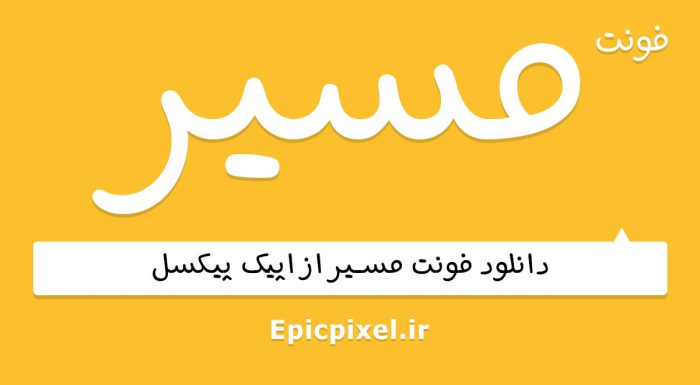
۵ فونت مسیر فارسی Massir
فونت های رایگان می توانند ابزارهای ارزشمندی برای طراحان باشند، به خصوص زمانی که سبک های متنوعی را ارائه می دهند. مجموعه ای که شامل سری فونت فارسی مسیر (A Massir) و نیز فونت های کلاسیک تر ابدو مسیر (Abdo Misr) است، چنین تنوعی را فراهم می کند. این مجموعه، فرصتی است تا با استفاده از سبک های متفاوت و کاربردی، به صورت رایگان، پروژه های خلاقانه خود را غنی تر کنید و جلوه ای خاص به طراحی های فارسی و عربی ببخشید.
کشف سری فونت های A Massir: سبکی الهام گرفته از دیوار نویسی
بیایید نگاهی دقیق تر به سری هنری A Massir داشته باشیم. این قلم فارسی اصالتاً یک فونت عربی بوده است که زحمت تبدیل و تطبیق آن برای زبان فارسی را آقای علی سواری کشیده اند. نکته برجسته و عاملی که فونت مسیر را از سایر فونت ها متمایز می کند، سبک بصری خاص و جسورانه آن است که به آن جلوه ای هنری و غیررسمی می بخشد و حالتی پویا و زنده به متن می دهد.
دو فونت از این سری که به صورت رایگان برای دانلود در دسترس هستند، با نام های A Massir Ballpoint Regular و A Massir Spray Regular ارائه می شوند. نام های این دو فونت خود گویای الهام گیری عمیق از حالت دیوار نویسی و اسپری رنگ هستند. در توضیحات این فونت به وجود دو نسخه کلی “ساده” و “دیواری نویسی شده” اشاره شده است؛ احتمالاً فونت های Ballpoint و Spray نمونه های برجسته یا زیرمجموعه هایی از سبک دیواری نویسی شده این خانواده هستند که با جزئیات و بافت های متفاوت ارائه شده اند تا شبیه سازی دقیق تری از نوشتار با قلم مو یا اسپری روی دیوار داشته باشند.
دانلودفونت مسیر با فرمت استاندارد و سازگار TTF ارائه شده و شامل تمامی حروف مورد نیاز زبان فارسی است. قابلیت استفاده در تمامی نرم افزارهای طراحی گرافیکی، این فونت گرافیکی را برای کاربردهای متنوعی چون طراحی های گرافیکی کلی، خلق لوگوتایپ های خاص و به یادماندنی، تیتر نویسی های چشمگیر در پوسترها و بنرها، و حتی آنچه در منبع اصلی “خوشنویسی” نامیده شده (احتمالاً به معنای استفاده در ترکیب بندی های نوشتاری هنری)، مناسب می سازد. استفاده از این فونت زیبا با سبک متمایز دیوارنویسی برای پروژه های تبلیغاتی و تجاری به زبان فارسی، جلوه ای خاص و متفاوت به کار شما خواهد بخشید و توجه مخاطب را جلب خواهد کرد.
هدیه ای اضافی در مجموعه: فونت های چند وزنی Abdo Misr
جذابیت این مجموعه رایگان تنها به فونت مسیر محدود نمی شود. در کنار این قلم هنری با سبک دیوارنویسی، می توانید از فونت های Abdo Misr نیز بهره مند شوید که در همان بسته به صورت رایگان گنجانده شده اند.
فونت ابدو مسیر در ۳ وزن متفاوت شامل بلک (Black)، بولد (Bold) و لایت (Light) قرار داده شده است. این وزن ها، تنوع بیشتری را به مجموعه اضافه کرده و امکان استفاده از فونت هایی با ظاهری متفاوت و کلاسیک تر از سبک دیوارنویسی مسیر را در همان پروژه یا پروژه های دیگر فراهم می کنند. فونت های Abdo Misr با داشتن وزن های مختلف، برای ایجاد سلسله مراتب بصری در متن و استفاده در بخش های مختلف یک طراحی، از عناوین فرعی تا بدنه متن های کوتاه، بسیار کاربردی هستند و مکملی عالی برای سبک نمایشی فونت A Massir محسوب می شوند.
در نهایت، این مجموعه رایگان که شامل دو فونت A Massir Ballpoint و A Massir Spray با سبک دیوارنویسی متمایز و فونت های چند وزنی Abdo Misr (بلک، بولد، لایت) است، یک پکیج جذاب و کاربردی برای هر طراح فارسی زبان محسوب می شود و امکان افزودن تنوع بصری به پروژه های گوناگون را بدون هزینه فراهم می آورد.